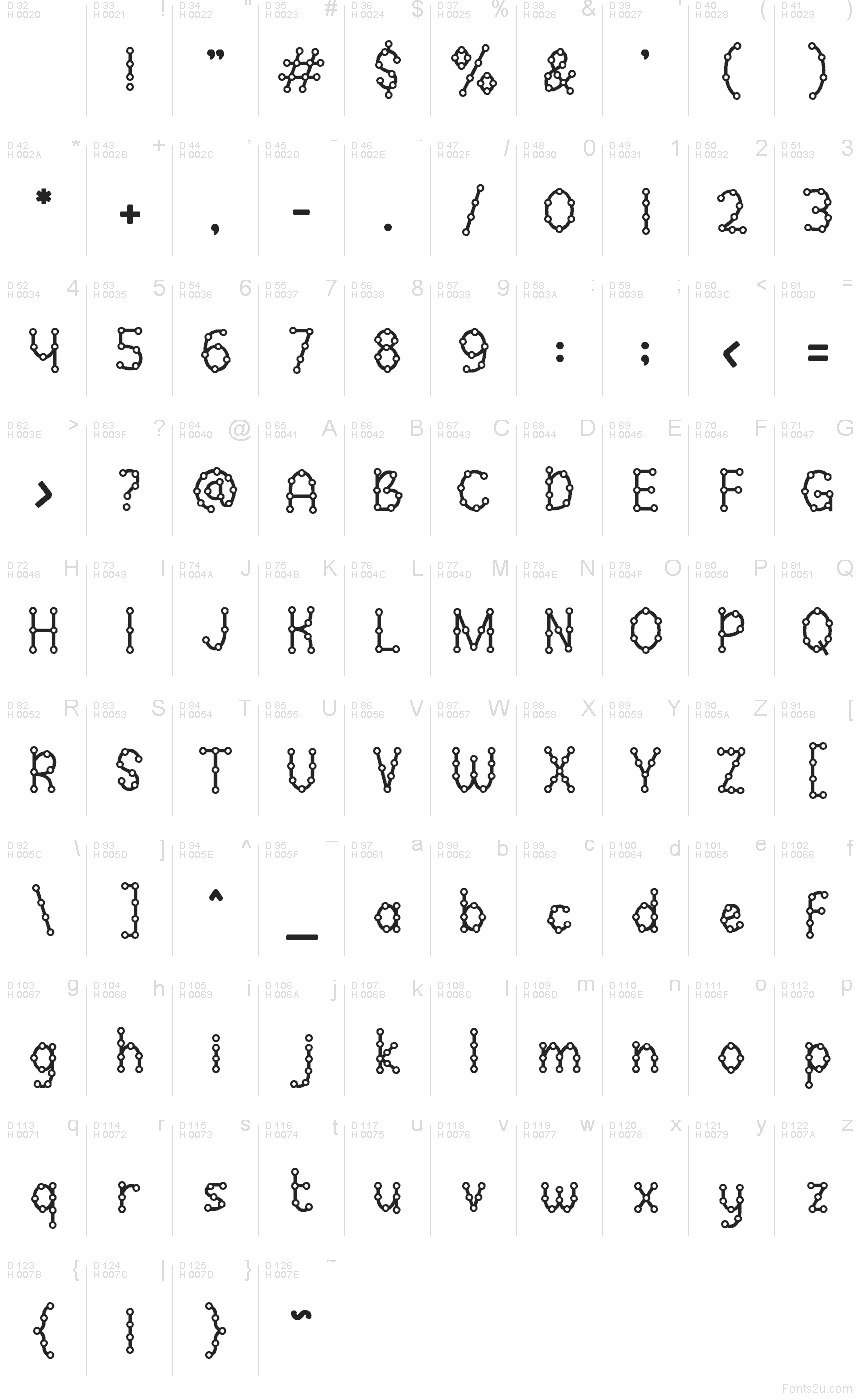
Clever Science Link
Clever Science Link von Putracetol Studio ist eine kostenlose Molekular-Display-Schrift mit einem spielerischen Labor-Charakter. Die Buchstaben bestehen aus dicken, abgerundeten Strichen, die durch offene Kreise verbunden sind. Dadurch wirkt das Alphabet eher wie eine Kette von Atomen oder ein einfaches Chemiemodell als wie gewöhnliche Schriftzeichen – abgerundet durch einen freundlichen, handgefertigten Schwung, der das Design leicht und lebendig hält.
Damit eignet sich diese kostenlose Schriftart hervorragend für STEM-Poster, Unterrichtsmaterialien, Kinderbuchcover, Experimentierkästen und das Branding für Wissenschaftsmessen. Sie funktioniert zudem bestens für kurze Überschriften, Titelkarten und logoartige Schriftzüge, bei denen der Rhythmus der verbundenen Punkte das Konzept bereits für sich trägt.